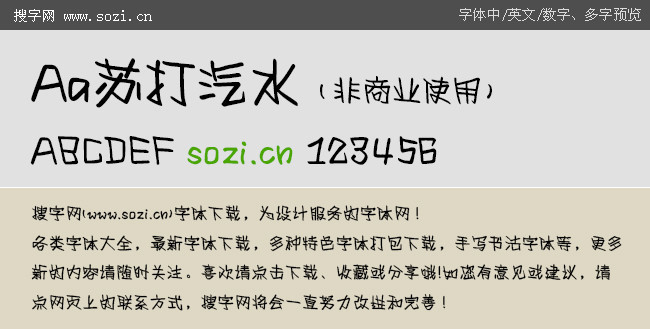
Aa蘇打汽水(非商業(yè)使用)
搜字網(wǎng)給大家提供一款A(yù)a蘇打汽水(非商業(yè)使用)中文字體下載,該字體線條粗細(xì)適中,字形比較張揚,卡通味實足,適合包裝畫冊等兒童卡通宣傳廣告等應(yīng)用(此字體為個人非商用版,商用可以聯(lián)系QQ:1006760504)。